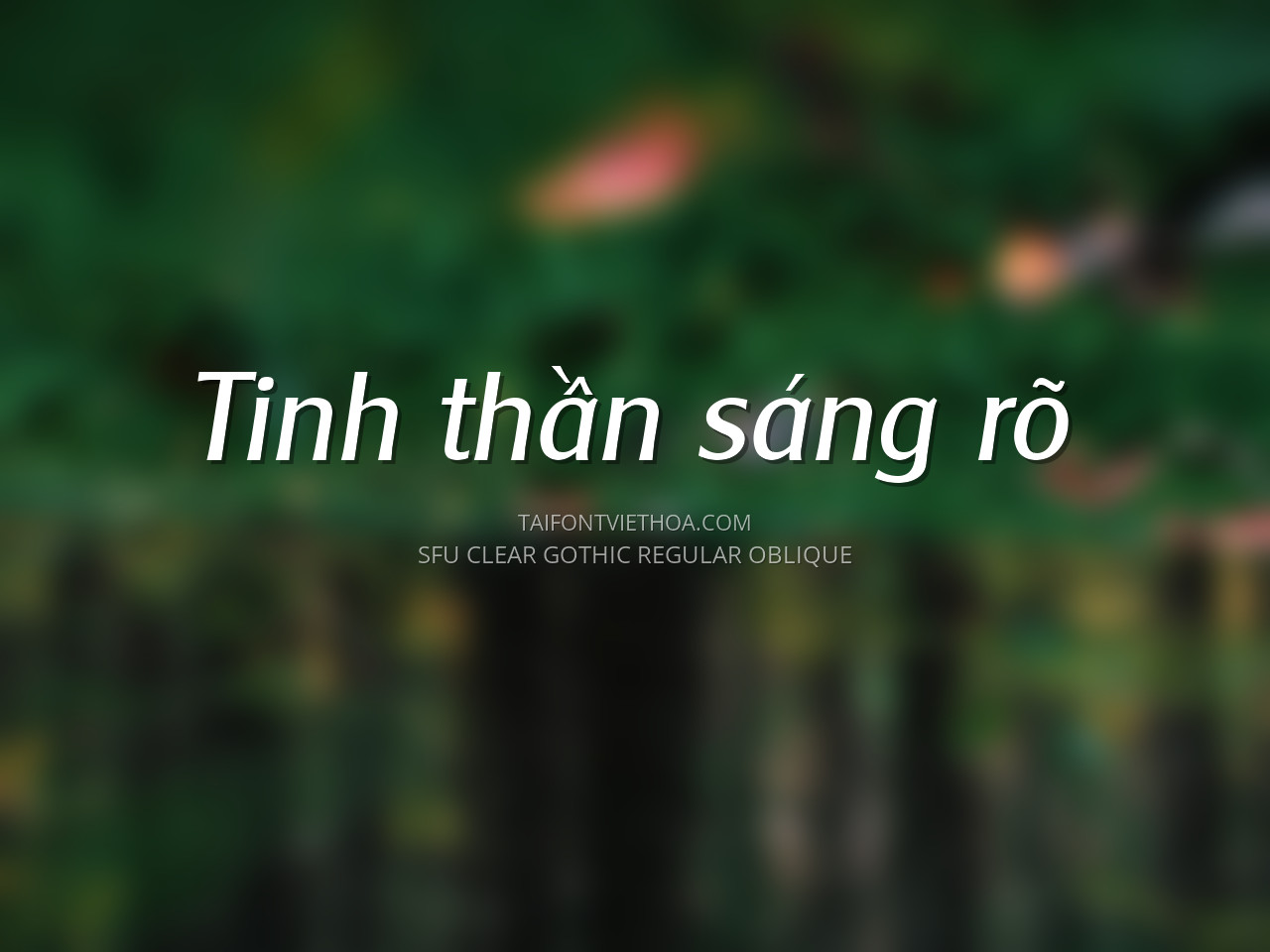
Giới thiệu về font SFU Cleargothic – Kiểu chữ Gothic hiện đại, dễ đọc và linh hoạt
SFU Cleargothic là phiên bản Việt hóa của font Clear Gothic – một biến thể sans-serif có chân nhẹ (semi-serif) hoặc transitional gothic, mang đặc điểm kết hợp giữa cấu trúc Gothic cổ điển và nét hiện đại trong thiết kế tối giản. Font có nguồn gốc từ thế kỷ 20, được ứng dụng trong các ấn phẩm in ấn, báo chí và quảng cáo nhờ khả năng hiển thị rõ nét, dễ đọc và truyền tải nội dung hiệu quả ở mọi kích thước.
Thiết kế rõ ràng – cân bằng giữa cổ điển và hiện đại
SFU Cleargothic có cấu trúc chữ cao, thẳng, các nét dày vừa phải và khoảng cách ký tự được tối ưu hóa giúp dễ đọc khi in với mật độ lớn. Nét chữ hơi vuông vức ở đầu, kết hợp cùng các đường cong nhẹ giúp kiểu chữ trở nên trung tính và dễ ứng dụng. Dù mang tên “Gothic”, nhưng font không quá sắc sảo hay trang trọng, mà thiên về tính ứng dụng thực tế, mang lại cảm giác thân thiện và chuyên nghiệp.